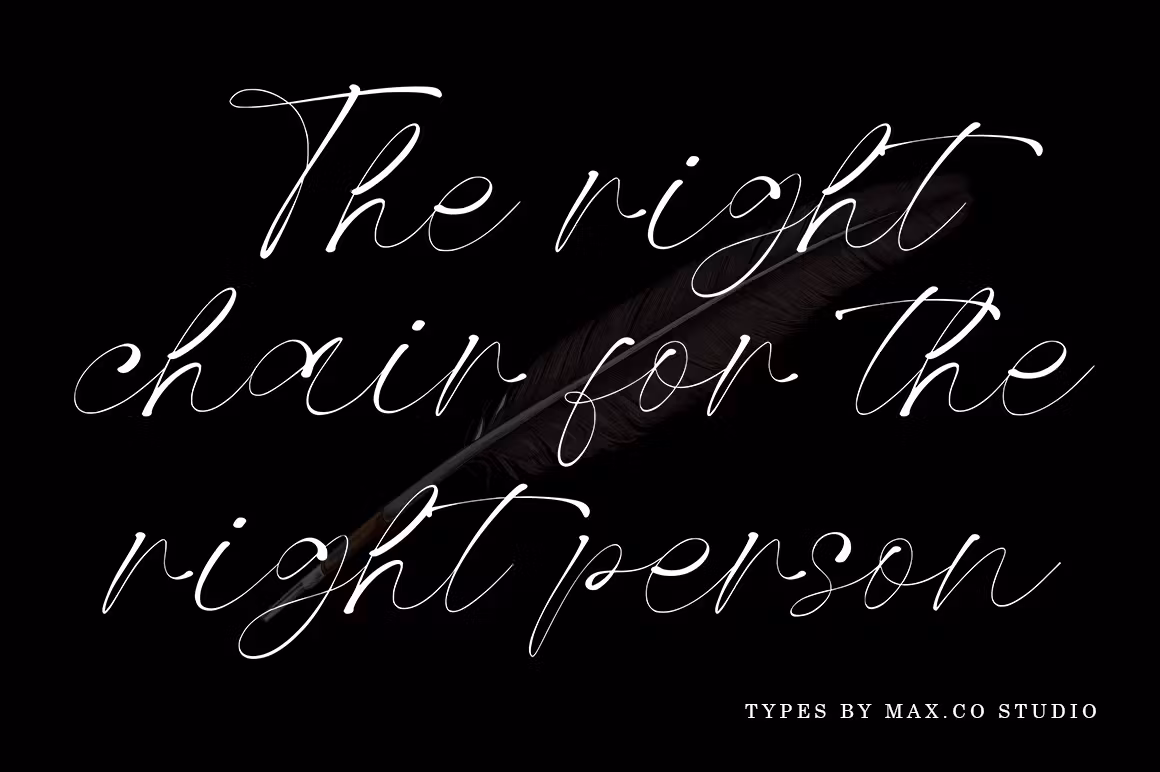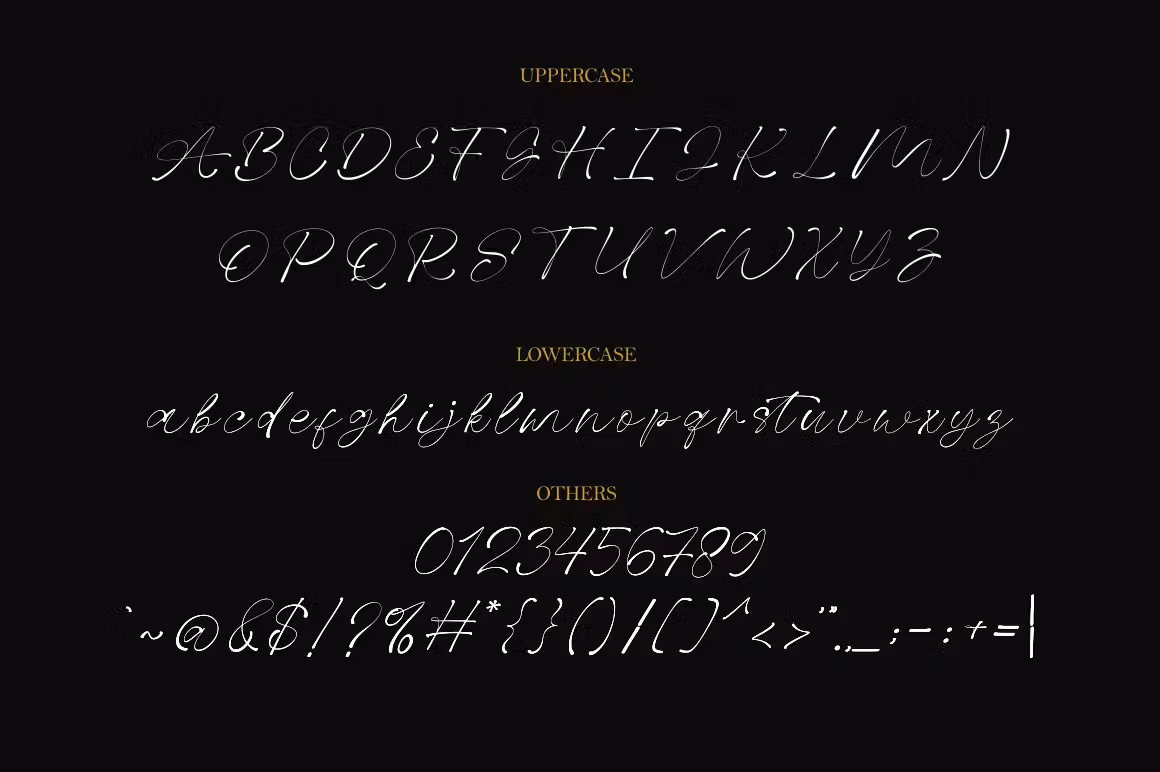
Bintang Font
La police Bintang Script tire son inspiration de l’รฉcriture classique des livres, ajoutant une touche moderne ร  son style script. Cette police est รฉquipรฉe de diffรฉrentes options, y compris des alternatives, des ligatures et une prise en charge multilingue. Cela enrichit l’aspect visuel et rend votre travail plus captivant. Cette police conviendra parfaitement ร  tous vos projets crรฉatifs :
du logo aux citations imprimรฉes, des invitations aux emballages de produits, des en-tรชtes au papier ร  lettre, sans oublier les vรชtements ou la conception web. Elle sera รฉgalement idรฉale pour les magazines et les livres.
Bintang Calligraphy Font